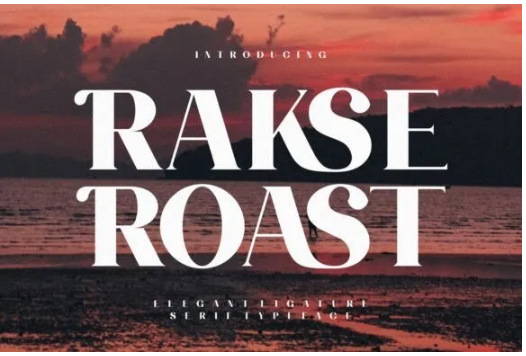
Rakse Roast - это элегантный и современный шрифт без засечек.
Этот минималистичный и чистый шрифт может быть легко применен в ваших любимых дизайнах, таких как обложки книг, журналы, посты в социальных сетях, приглашения и многое другое!
Rakse Roast - это элегантный и современный шрифт без засечек.
Этот минималистичный и чистый шрифт может быть легко применен в ваших любимых дизайнах, таких как обложки книг, журналы, посты в социальных сетях, приглашения и многое другое!